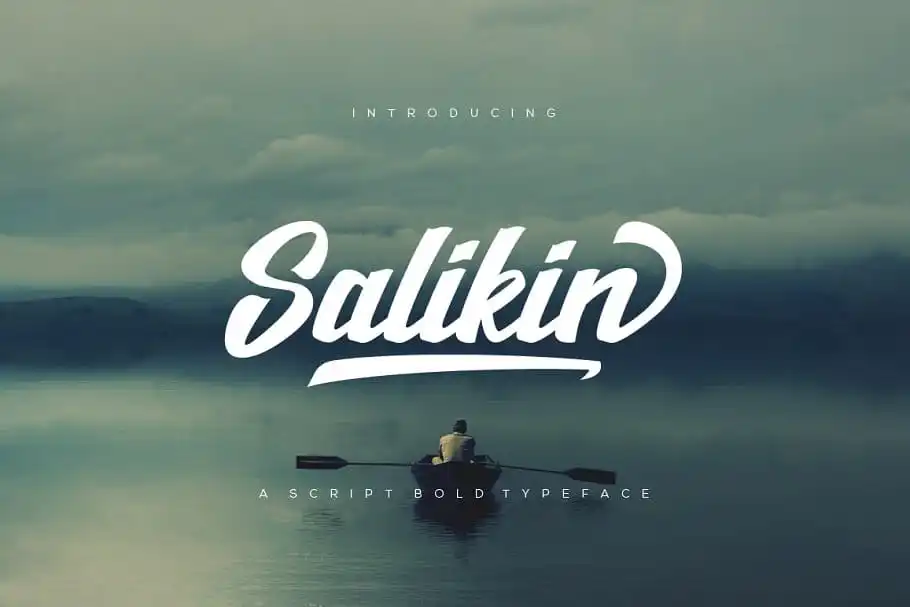
Nós temos a agradável oportunidade de apresentar para vocês a Salikin Bold Script Font, uma excelente escolha para aqueles que procuram um estilo elegante e moderno. Esta fonte é perfeitamente caracterizada como um tipo de letra script bold, repleta de personalidade e sofisticação. A Salikin oferece um estilo bold com toques de estilo brush, o que torna-a uma opção ideal para design gráfico variado. Ideal tanto para uso em logotipos quanto no cabeçalho de websites, a Salikin é um recurso extremamente valioso para designers de moda, etiquetas, nomes de camisetas, mensagens e embalagens. Essa fonte, tão versátil quanto bela, será certamente uma escolha adequada para qualquer projeto que necessite de um toque especial e único. A Salikin foi projetada pelo designer zziplex e é uma das fontes script bold mais desejadas no mercado atual. Ela traz a sofisticação dos estilos brush com o poder do tipo bold, tornando-a uma escolha ideal para qualquer projeto que exigir um toque diferenciado. Descubra a beleza da Salikin e deixe seu design se destacar!